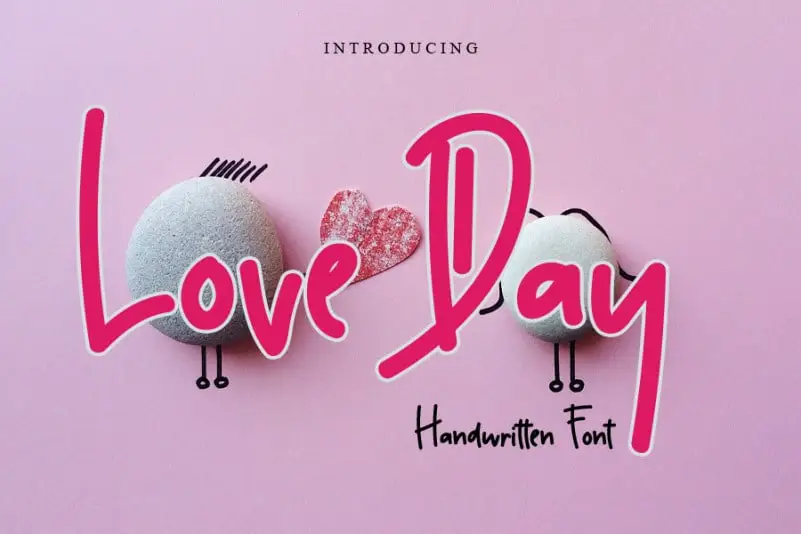
Love Day Handwritten Font – Download Grátis
A fonte ‘Love Day Handwritten Font’ é uma sugestão perfeita para quem procura um toque romântico e criativo para seus projetos gráficos. Com sua abordagem delicada e encantadora, essa font pode ser usada em diversos tipos de designs, desde as cartas matrimoniais até os elementos personalizados que tornam qualquer projeto único e singelamente especial. Ideal para quem valoriza a expressão pessoal no design visual, esta font representa uma maneira elegante e divertida de incluir o amor e a emoção em projetos como invitations de casamento ou cartas de agradecimento. Escolha ‘Love Day Handwritten Font’ para dar um toque singelo e inconfundível aos seus designs pessoais ou profissionais, garantindo uma sensação de delicadeza e encanto que certamente chamará a atenção dos espectadores.